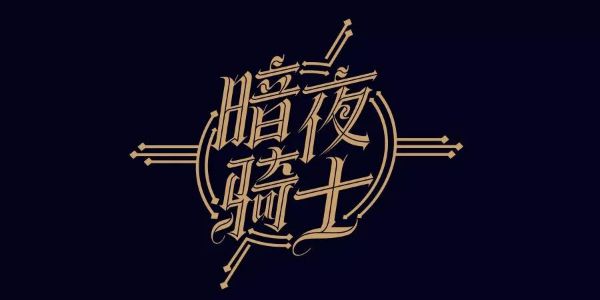
Get!如何西文中用造一款哥特字
本周给大家带来的是一篇字体设计的教程。重点在于通过这个案例,带大家认识西文中用的造字法。首先我们来看一下倍速播放的演示视频吧!
视频看完了我们看一下重点,西文中用的三大步骤,如下。
下面我们将这三点分别说明。
确定字型实际上就是通过分析项目需求的风格特征,来确定一款适合此项目风格的西文字体。
比如我们这次做的是“暗夜骑士”四个字,首先要做的是分析适合这个主题的风格和形式,切忌一上来不经过分析思考就开始做。
通过联想,我们可以从“暗夜骑士”发散出很多关键词,如下。
通过这些关键词我们可以很自然的联想到哥特字型,ok,那我们就在软件中输入所有英文字母和数字的大小写,如下。
接下来我们去选择几款哥特字型去进行比对,不同的哥特字型写法和风格也是有差异的,所有我们要选择一个最合适的。
这里我挑了四款哥特字型来进行比对,如下。
可以看到不同的哥特字,其大小宽窄还有一些写法都是不同的,我想将“暗夜骑士”做成有哥特风但同时又不会那么死板的感觉,所以选择了第三款哥特体。
这款笔画相对其他几款更为飘逸张扬,所以选择了这款。至此我们的字型就确定好了,接下来进行第二步“提取笔画”。
提取笔画就是将西文中的字母或部分特征提取出来,用来拼凑中文字。具体该怎么做呢?可以先将“暗夜骑士”四个字用正体字打出来,观察这几个字所用到的笔画。
正体字也就是结构非常严谨的字,常规的黑体、宋体都属于正体字的范围。
这里我用了思源宋体-Bold字重作为结构的参考字。
输入好之后们可以对字做笔画的拆分,找出构成这几个字最基本的笔画,如下。
通过拆分可以看出这整组字是用 横、竖、竖勾、点、捺、提和不同程度的撇构成的。到此我们便可以从英文中去找类似结构的笔画,如下。
通过小写“l”和“i”得到横竖笔画,如果将竖笔的特征加长就是一个勾的笔画。
通过大写“I”和小写“f”得到提(也可以当横的另一种变化笔画)和点。
通过小写“J”的笔画提取出顶部的特征,然后用钢笔画出撇笔的特征,延长尖叫锚点的长度可以得出不同程度的撇,而将撇旋转一下就可作为捺的笔画。
这里也提醒大家不要学死了,如果英文字母中没有合适的笔画就需要我们运用他们的特征自己去做,就像上面的“撇”一样。另外如果英文字母中的曲线不平整也是需要我们去调整或者重新去画的。
到此文字中需要的笔画都提取完毕了,接下来就是第三步“字形重组”了。
字形重组,就是用我们提取出来的笔画重新组成字形,如下。
我们可以先选择一种笔画复制到所有的文字上,再去调整不同笔画的长短即可。这样做比较有效率。另外在交叉转折的横笔我们是看不到哥特体特征的,这种时候可以直接用矩形表示。
接下来再把竖笔放上去,注意边做边调整,灵活一点,比如这里“口”字的横笔就去掉了,而是用两个竖笔的特征去做延伸。
依次将提取出来的笔画放上去,字体也就渐渐成型了。做成这样并不是就结束了,我们需要根据视觉对字的结构进行严谨的调整,让视觉上更舒服。
图中白色部分是原始的字形结构,而金色部分是调整后的,这样一对比结构差异还是比较大的。
调整完结构后可以做一做排版跟变化,让其在视觉上更有冲击力。
也可以加入一些更有形式感的特征,比如这里我将笔画从中间切割一下,使其更具有形式感。
至此我们的哥特字也就做完了。那么西文中用的方法大家学会了嘛?